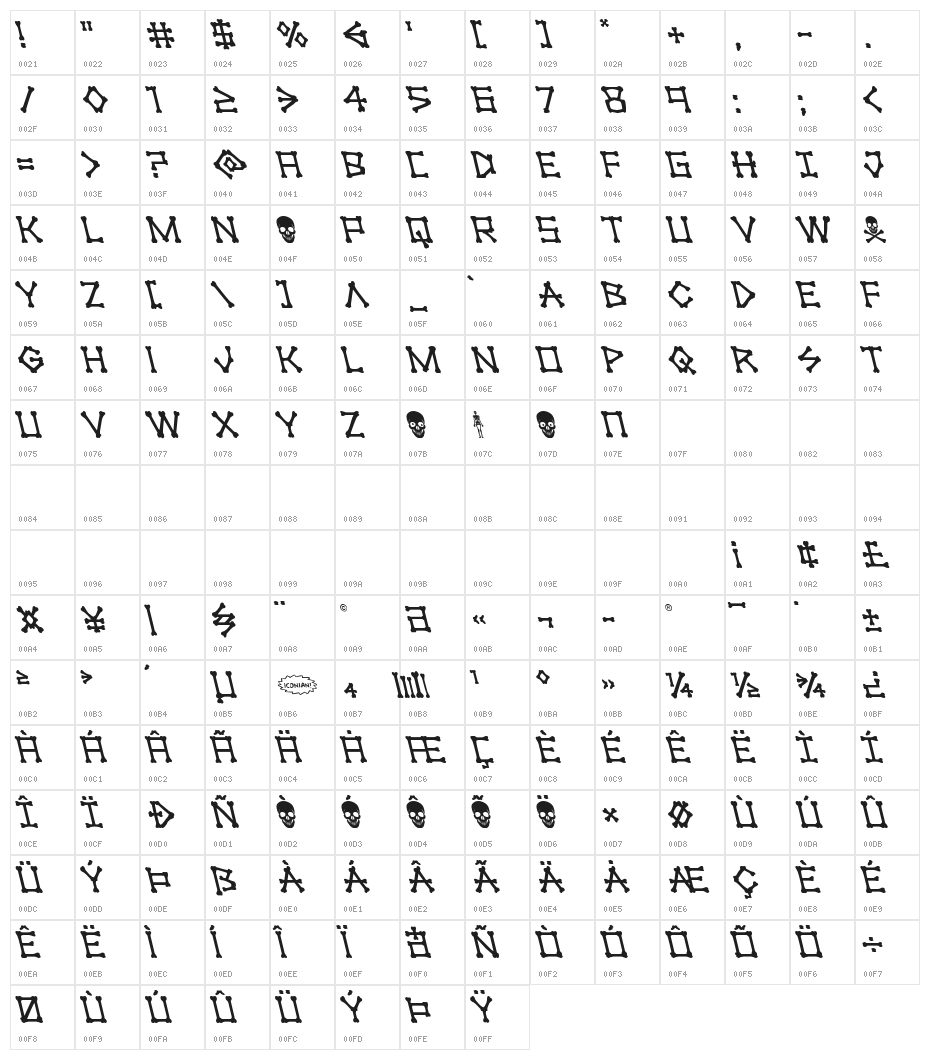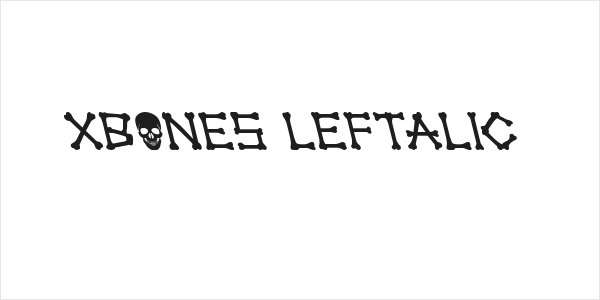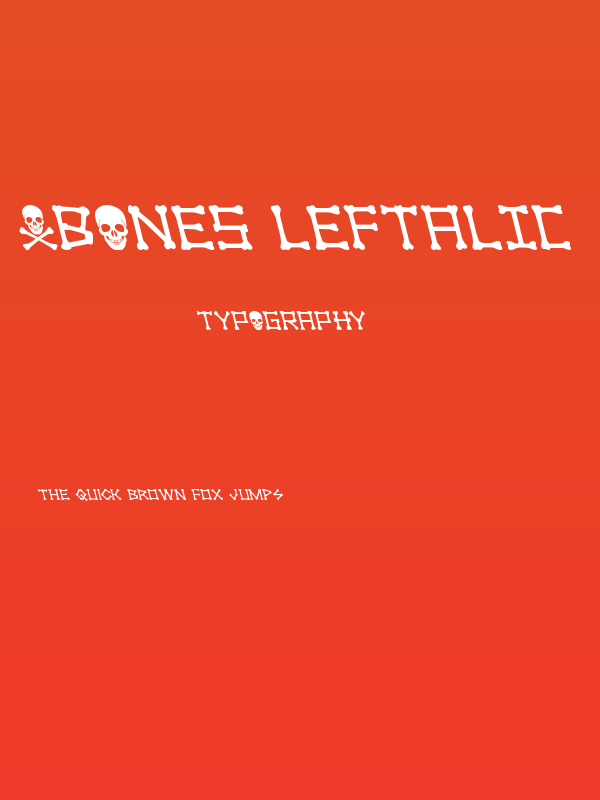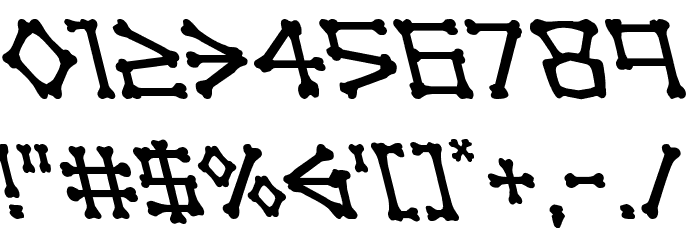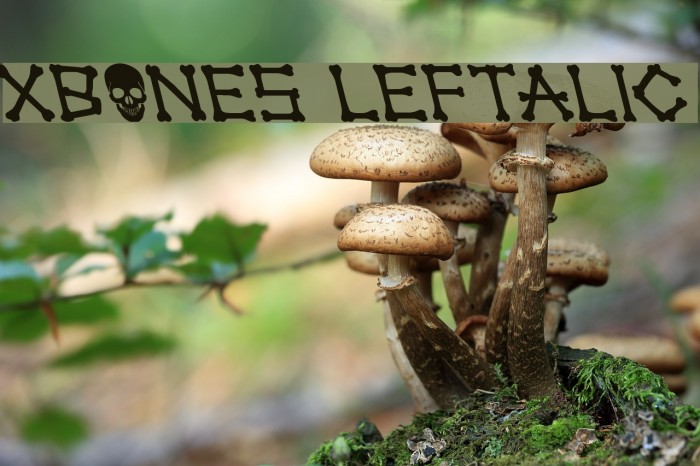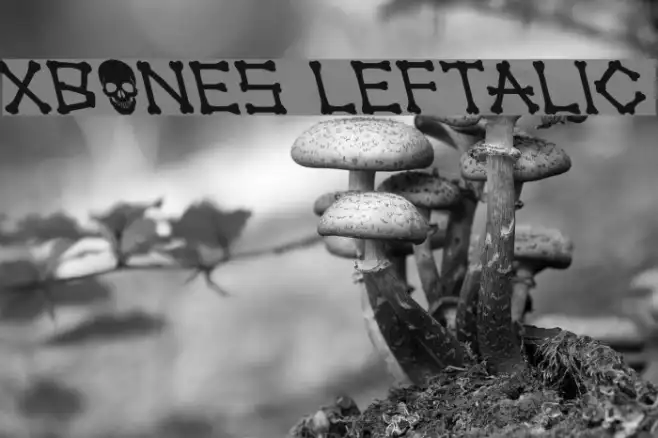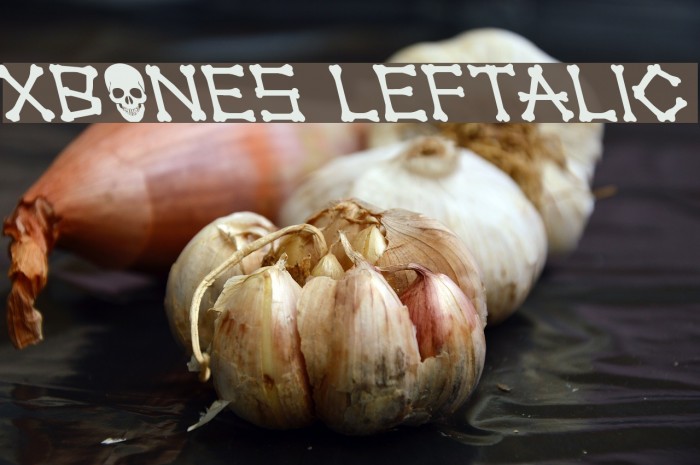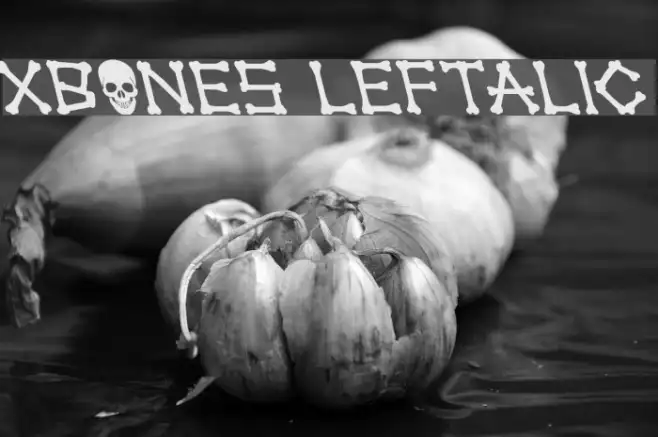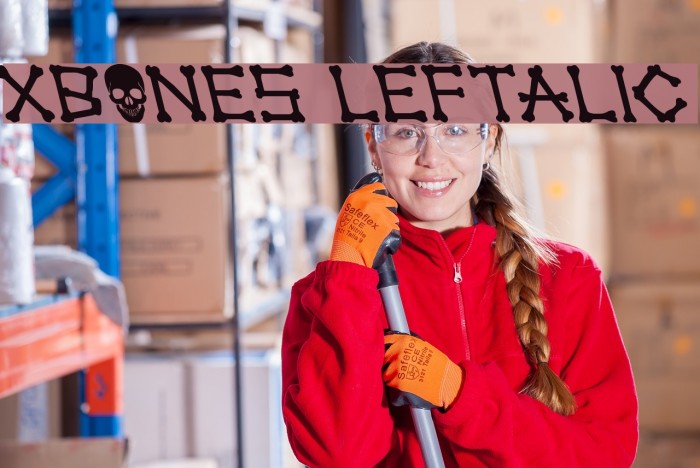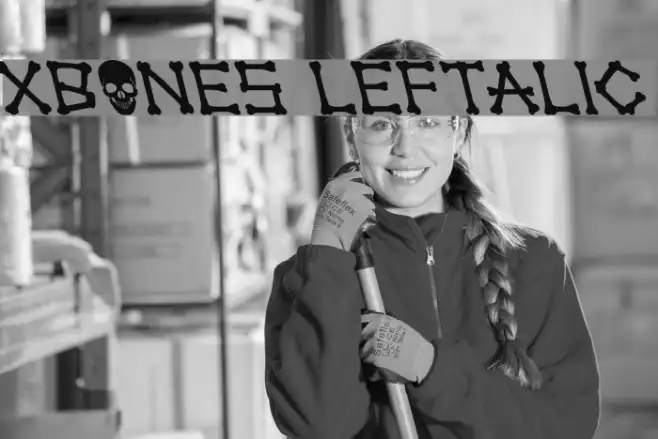
xBONES Leftalic Font
| Caso de uso | Headlines, Logos, Themed Events |
| Proyectos propuestos | Ideal for Halloween-themed projects, children's books, party invitations, and any design requiring a quirky, spooky touch. |